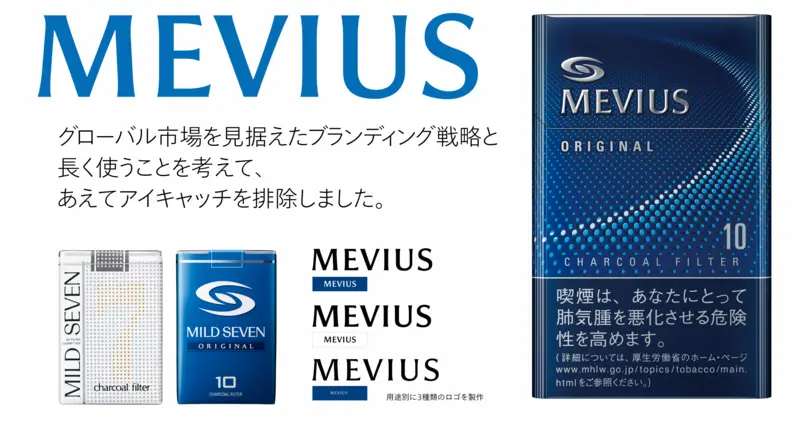
事例のご紹介:MEVIUS
「MEVIUS」は世界的な市場を前提に、モノタイプ社タイプディレクター小林章がロゴデザインを担当しました。
長く使うことを考えて、あえてアイキャッチを排除し、落ち着いた印象のデザインを採用しまた。これまで日本の大手企業が取らなかった海外にも新ブランド浸透を図るブランディング戦略と言えます。